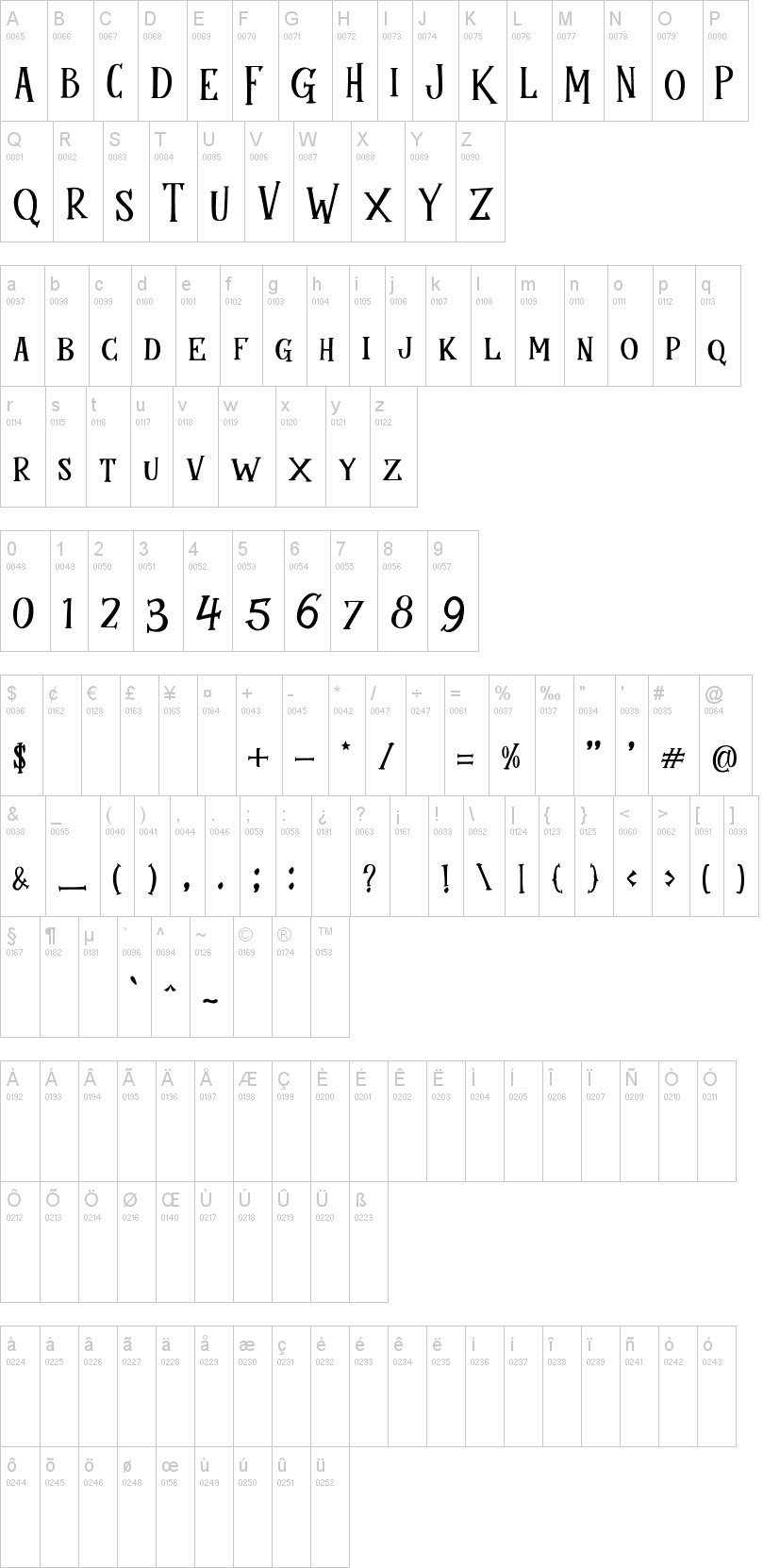
Mukadua
Mukadua 字体是一种现代手写字体,它的特点是笔画明显,线条流畅,具有极强的视觉冲击力。该字体适用于许多设计领域,例如标志、包装、海报、书籍封面、品牌标识等等。 Mukadua 字体由一组大胆、简洁的字母组成,包括了大写字母、小写字母、数字和标点符号。该字体的设计师还为每个字符添加了一些额外的笔画和装饰,以增强字体的个性化和创意性。 Mukadua 字体可在许多设计软件中使用,例如 Photoshop、Illustrator、InDesign 等等。此外,该字体也可用于网页设计和移动应用程序设计中。
Mukadua是一款非常不错的手写艺术字体,具有很好的视觉感,适合于文化类的宣传设计、商业类品牌的广告和产品包装设计以及个性化文字排版等较多场景。